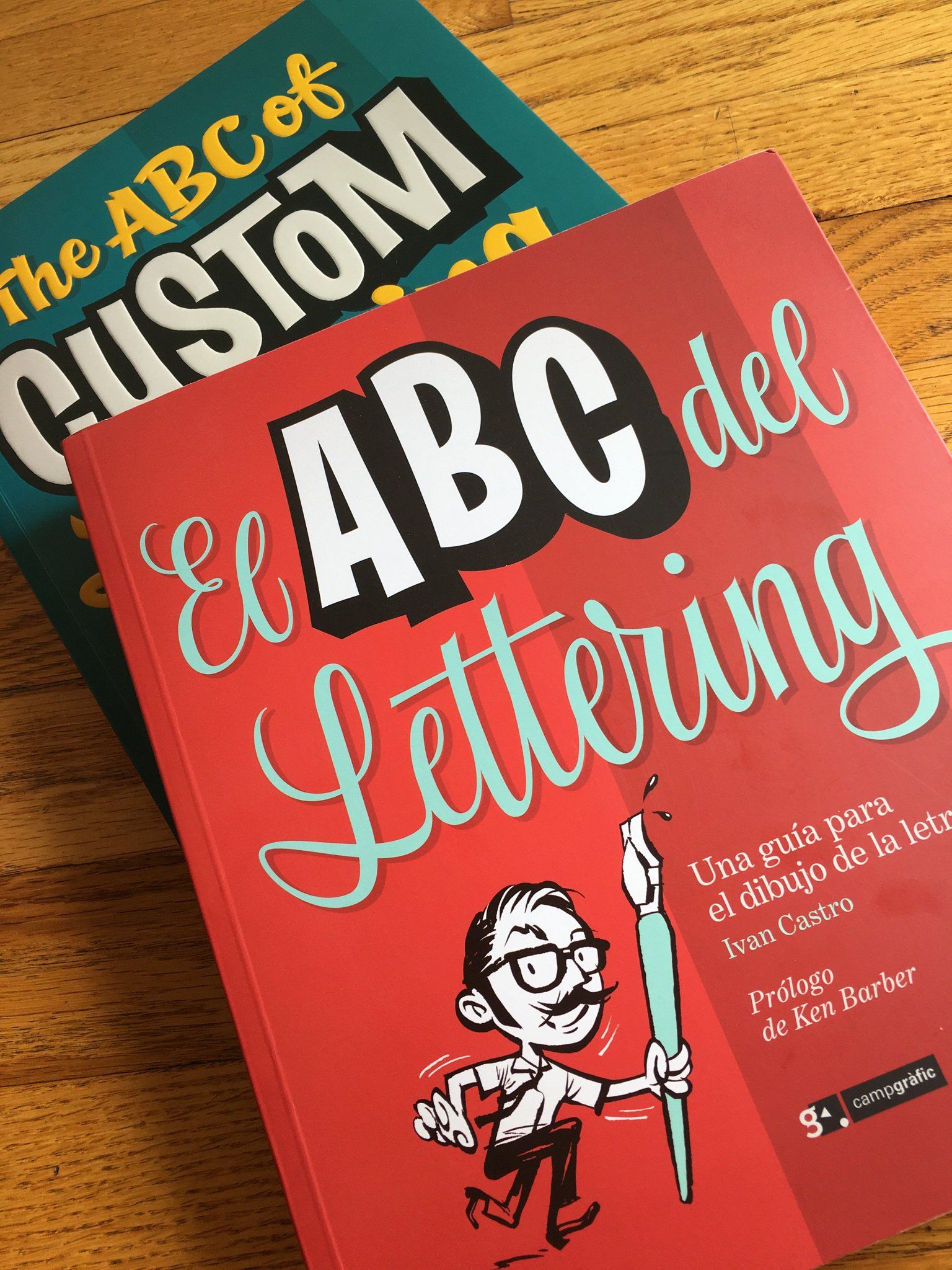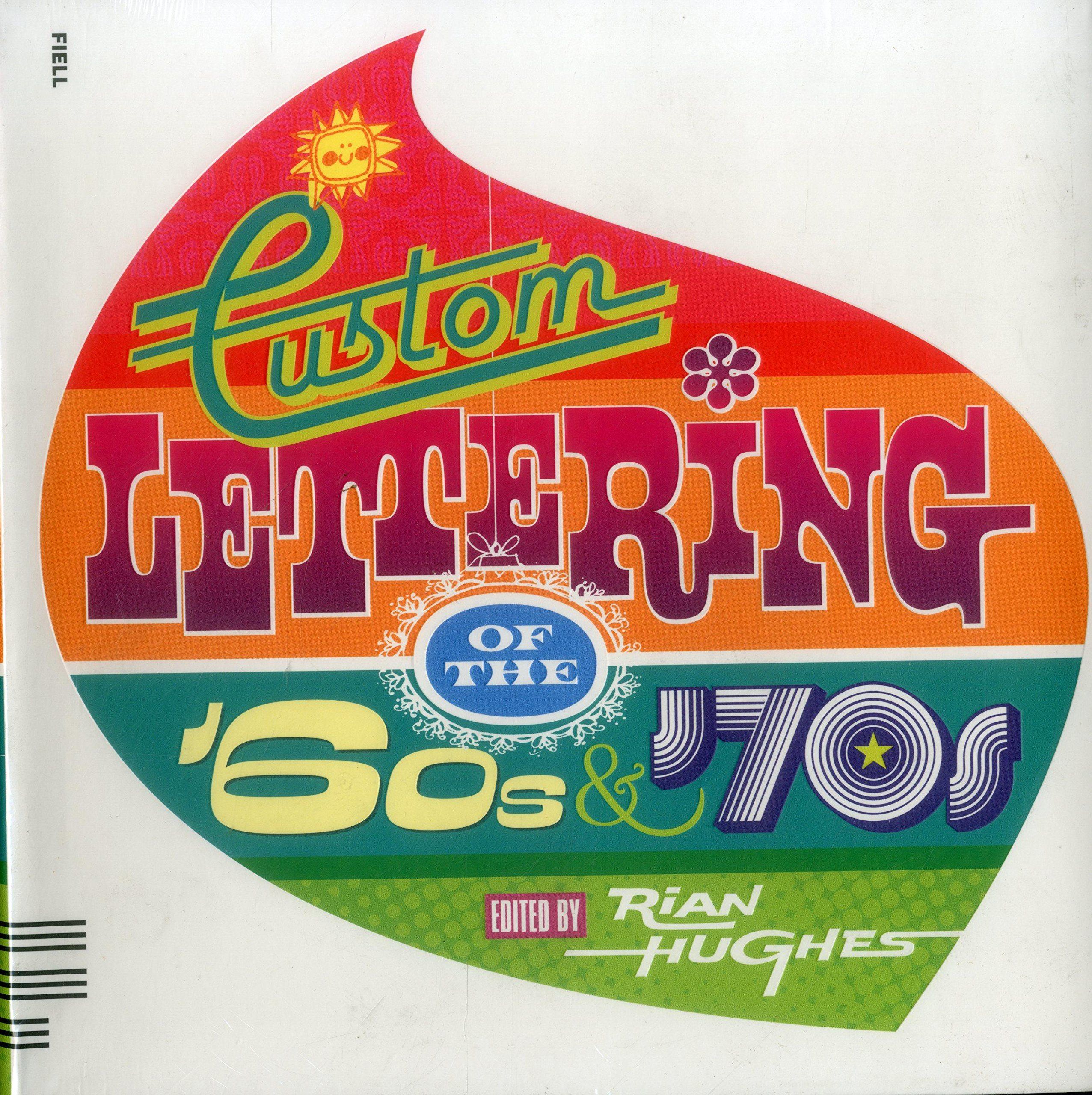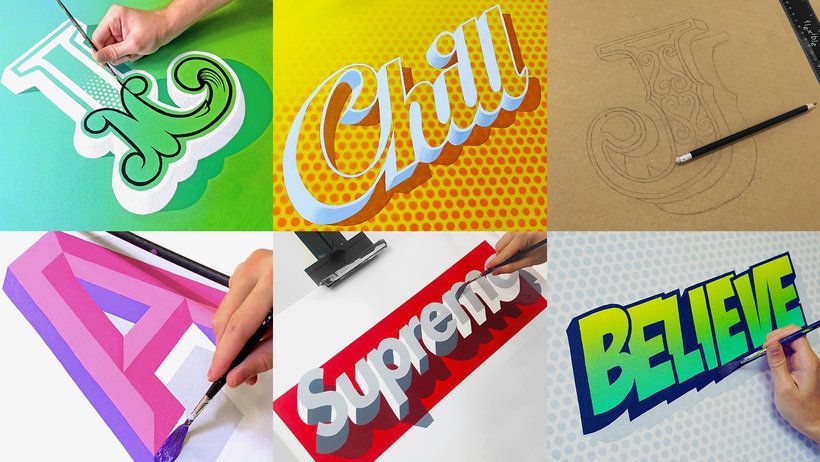
5 libros de lettering y tipografía para inspirar tus proyectos
El artista del lettering James Lewis comparte contigo algunos de sus libros de referencia
James Lewis (@jamesllewis) siempre pensó que su letra era fatal, así que se propuso mejorarla. Fue así que inició su carrera en el mundo de las letras y la caligrafía, que lo ha llevado a colaborar con marcas como BBC, Amazon o Montblanc.
Para cualquier diseñador, es indispensable armarse de una biblioteca de referencia e inspiración. Por ello, hoy James comparte contigo 5 libros esenciales sobre lettering y tipografía que también te acompañarán en tu camino:
Shadow Type: Classic Three-Dimensional Lettering, por Steven Heller y Louise Fili
Un libro perfecto para los amantes de los gráficos vintage, que recopila información de algunas de las tipografías más influyentes de los siglos XIX y XX. Las letras tridimensionales, con su estructura monumental y arquitectónica, formaron parte de periodos importantes de la historia de la tipografía. Encontrarás la explicación de más de 300 fuentes de distintos países, que sin duda te servirán como referencia e inspiración para tus propias creaciones.
Heller, S., Fili, L. (2013). ‘Shadow Type: Classic Three-Dimensional Lettering’, Thames and Hudson
El ABC del lettering, por Ivan Castro
El diseñador gráfico especialista en lettering Ivan Castro (@ivancastro) explica en este libro los conceptos básicos y técnicas imprescindibles para dominar esta disciplina. Sus métodos parten de más de una década de docencia en caligrafía, así como más de 15 años como conferencista, tallerista y orador en reconocidos festivales de diseño.
Castro, I. ‘El ABC del lettering’ (2016), Planeta
Expressive Type: Unique Typographic Design in Sketchbooks, in Print, and On Location around the Globe, por Alex Fowkes
En este libro se recopila el trabajo de importantes diseñadores de todo el mundo que usan la tipografía en campos tan diversos como el branding, la publicidad, el diseño de productos, así como proyectos personales. Además encontrarás briefs de la vida real para apreciar la forma en la que cada proyecto cobró vida.
Fowkes, A. ‘Expressive Type’, (2017), Rockport Publishers
Desining Type, por Karen Cheng
En este libro se aprecia la influencia de la tipografía en el diseño gráfico como todo, así como en la gráfica impresa. Es una fuente básica que explica los procesos por los que se diseñan tipografías y los componentes que las caracterizan: estructura, compensación visual, legibilidad y forma. Encontrarás diagramas explicativos, análisis de tipografías, signos de puntuación, números y más.
Cheng, K., ‘Designing Type’ (2006), Yale University Press
Custom Lettering of the 60s And 70s, por Rian Hughes
El autor celebra los estilos que nacieron a partir de la letra dibujada a mano en los sesenta y setenta, antes de la popularización de las computadoras. En estos años, los diseñadores experimentaron libremente con soluciones de diseño que además se caracterizaron por lo atrevido de la época. Encontrarás más de 4 mil ejemplos de lettering con efectos dramáticos y memorables que servirán de inspiración para diseñadores y estudiantes.
Hughes, R., ‘Custom Lettering of the 60s And 70s’, (2010), Fiell Publishing